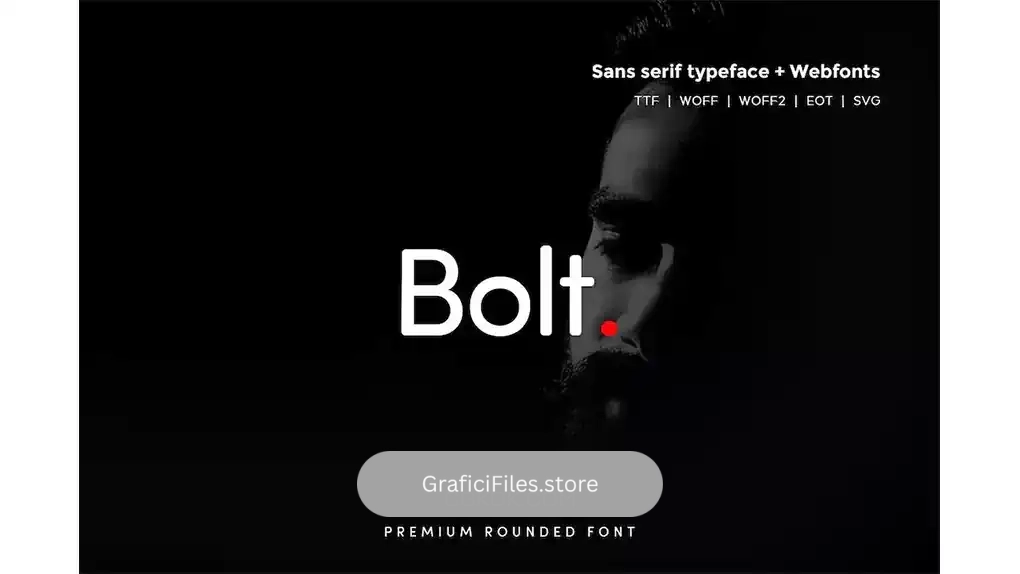
فونت انگلیسی ساده Bolt Rounded – Modern Typeface + WebFont : این مجموعه شامل یک فونت انگلیسی ساده و مدرن است که برای تایپوگرافی مناسب میباشد.
• سبک: Sans-Serif
• فضا بین حروف: معمولی
• اندازه بهینه: تمامی سایز ها